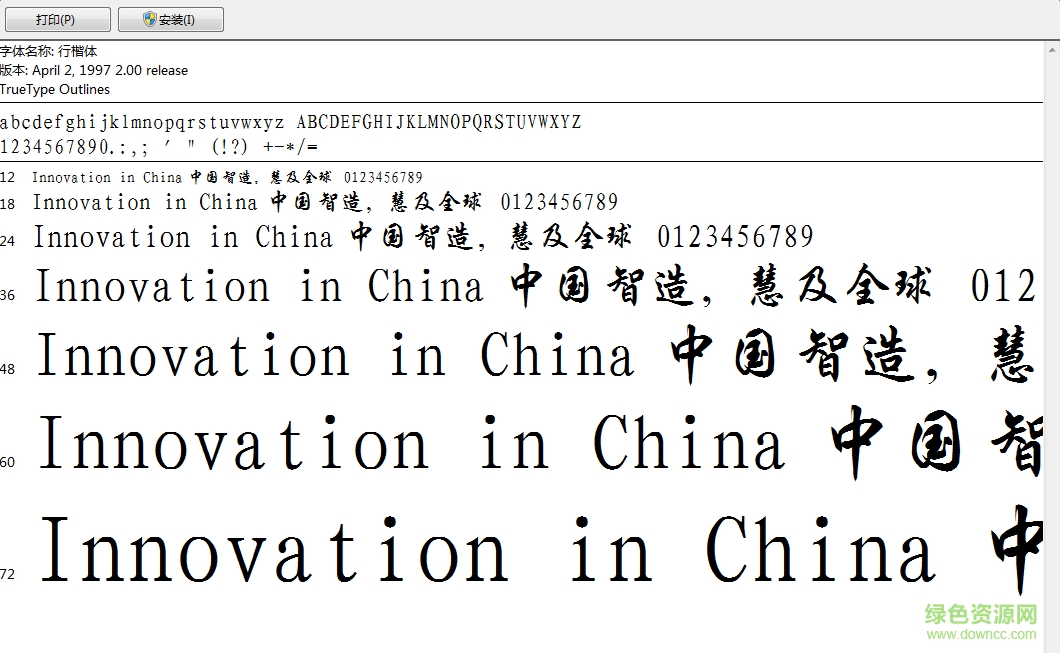
软件介绍 软件标签: 四通利方行楷体 四通利方 四通利方行楷体简是一款四通利方行官方为用户打造的四通利方行楷体简体字体,相信很多用户再找这款字体,现在绿色资源网为您免费提供下载,喜欢就不要错过!四通利方行楷体简字体背景:四通利方行楷体简是四通利方字体库中的一种字体,字体清新飘逸、苍劲有力,可应用于杂志报刊、文学创作、平面广告、印刷包装等领域,喜欢的朋友可免费下载收藏。安装使用方法:方法一:控制面板/字体/文件/安装新字体;方法二:直接将字体复制到C:WINDOWSFonts。方法三:针对win7系统以上,用户只需选中字体右键安装即可。注意事项:本站所有字体资源仅供个人学习与参考,如需商业使用请到相关官网授权。 软件截图 上一张下一张(1 / 1) 安装详细截图 猜你喜欢 行楷字体 楷书字体 行楷字体 行楷字体大全是绿色资源网小编为大家打包整理的行楷字体ttf合集,包含了几十款应用极广的行楷体,适用于影视、广告、平面、印刷各种行业领域,选择多样,下载便捷! 查看更多>> 汉仪苏泽立行楷精修版简 3.01M/中文/4.0/免费版下载 汉仪许静行楷字体 2.44M/中文/4.4/下载 繁体行楷字体大全 46.87M/中文/2.5/下载 经典行楷简体 常规 5.54M/中文/2.3/下载 文星简行楷 3.41M/中文/6.6/下载 方正字迹贺飞行楷字体 10.00M/中文/8.0/下载 楷书字体 楷书字体是绿色资源网小编专为大家收集的一类非常流行而且好用的楷书字体,它包括了各种形式的楷书。楷书也叫正楷、真书、正书。从程邈创立的隶书逐渐演变而来,更趋简化,横平竖直,笔势雄奇,姿态横生,可应用于绘画设计、艺术创作、平面广告、印刷包装、电视广告等等各行各业。也是现在很多行业必用的一类字体,小编收集的这一类楷书字体希望能更好的帮助大家收集和使用楷书字体。 查看更多>> 楷体国标字体官方版 2.45M/中文/7.1/下载 汉仪闪耀楷书字体 1.77M/中文/0.0/下载 华为汉仪锦时楷书 2.92M/中文/5.0/下载 楷书字典手机版 4.46M/中文/5.0/v2.0 安卓版下载 经典楷体繁体 3.96M/中文/5.0/下载 楷书繁体字体包 9.76M/中文/8.0/下载 其他版本下载 标题 大小 更新日期 下载 下载地址 电脑版 四通利方行楷体简 点击报错 软件无法下载或下载后无法使用,请点击报错,谢谢! 关闭报错反馈 请描述您所遇到的错误,我们将尽快予以修正,谢谢! *必填项,请输入内容 本类最新 rs_cuhei字体 rs_song2字体 rs cubiao字体 rs_tecuhei字体 rs_xingkai字体 rs_zongyi字体 用户评论 热门评论 最新评论 发表评论 查看所有评论(0) 昵称: 请不要评论无意义或脏话,我们所有评论会有人工审核. 字数: 0/500 (您的评论需要经过审核才能显示)